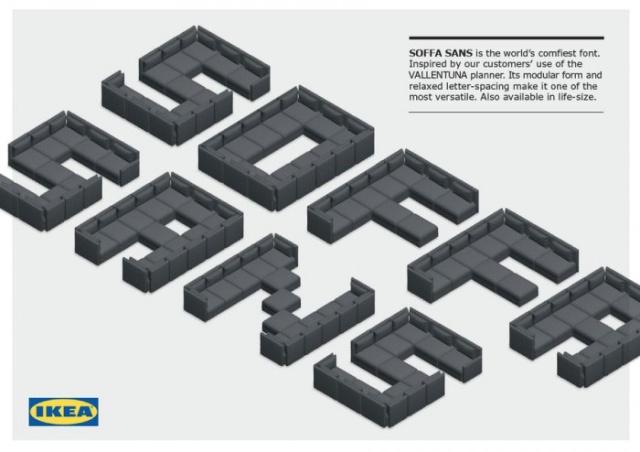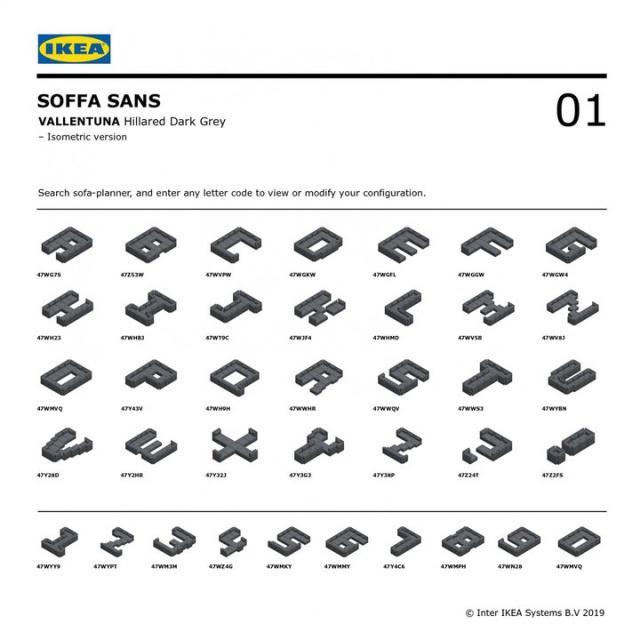
宜家推出“沙发字体”:现实中买齐整套需要92万元
以“Design your own sofa”(设计你自己的沙发)在线工具衍生出的模因为灵感,宜家(IKEA)近日发布了名为“Soffa Sans”的免费字体。该工具允许客户设计自己心目中最理想的沙发布局和配置,可以在Vimle系列到Vallentuna模块化沙发系列中任意选择。
原本这只是方便用户挑选的自定义设计工具,但随后用户发现可以在不限制成本的情况下实现任意配置,激发出了类似于Sims的创造力设计。在看到这项设计的独特潜力之后,宜家就数字代理商Proximity London合作创建了Soffa Sans字体。
宜家表示这是“世界上最舒适的字体”,能够以鸟瞰视角和斜视角用Vallentuna沙发来创造各种字母和文字。这套免费字体已经提供下载,共有白色、蓝色和灰色三种选择。此外The Drum表示Soffa Sans字体共使用了1434款产品,如果将字体中所用的沙发弄到现实生活中费用大约为106320英镑(约合920821.57元人民币)。